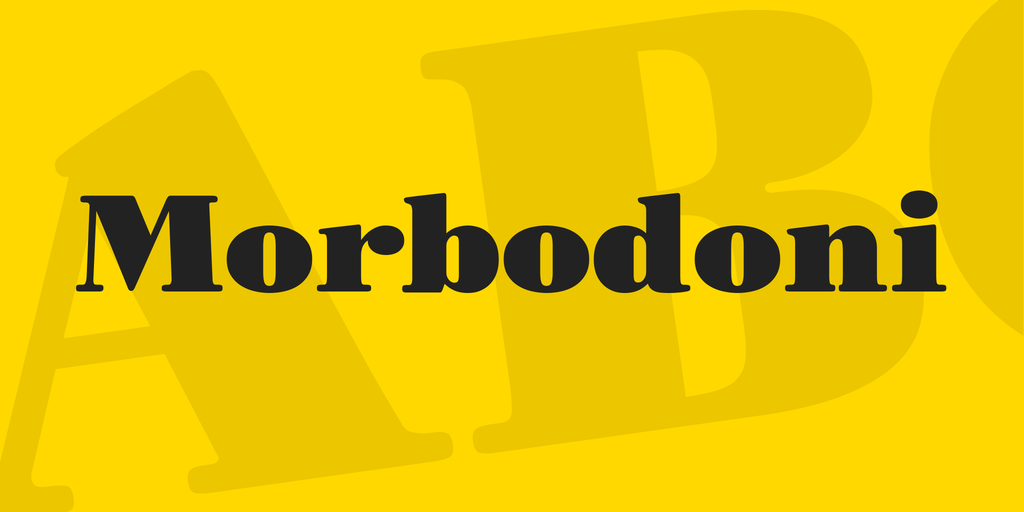
A Morbodoni é uma versão atualizada moderna das famosas tipografias ultra-fat Bodini. Esta nova face serif oferece cantos arredondados e traços ligeiramente mais grossos que permitem um contraste menor, facilitando a renderização web e trazendo uma aparência mais suave e elegante. Pertencente à família de fontes Fonticio Typeface, ela foi projetada para fornecer uma face serif com potencial para exibição em tela cheia, mas também excelentes características de renderização tanto offline quanto online. Esta fonte é um ótimo complemento para designers que buscam uma mistura moderna e sofisticada, adequada tanto para títulos grandiosos quanto para textos legíveis e agradáveis ao olho.